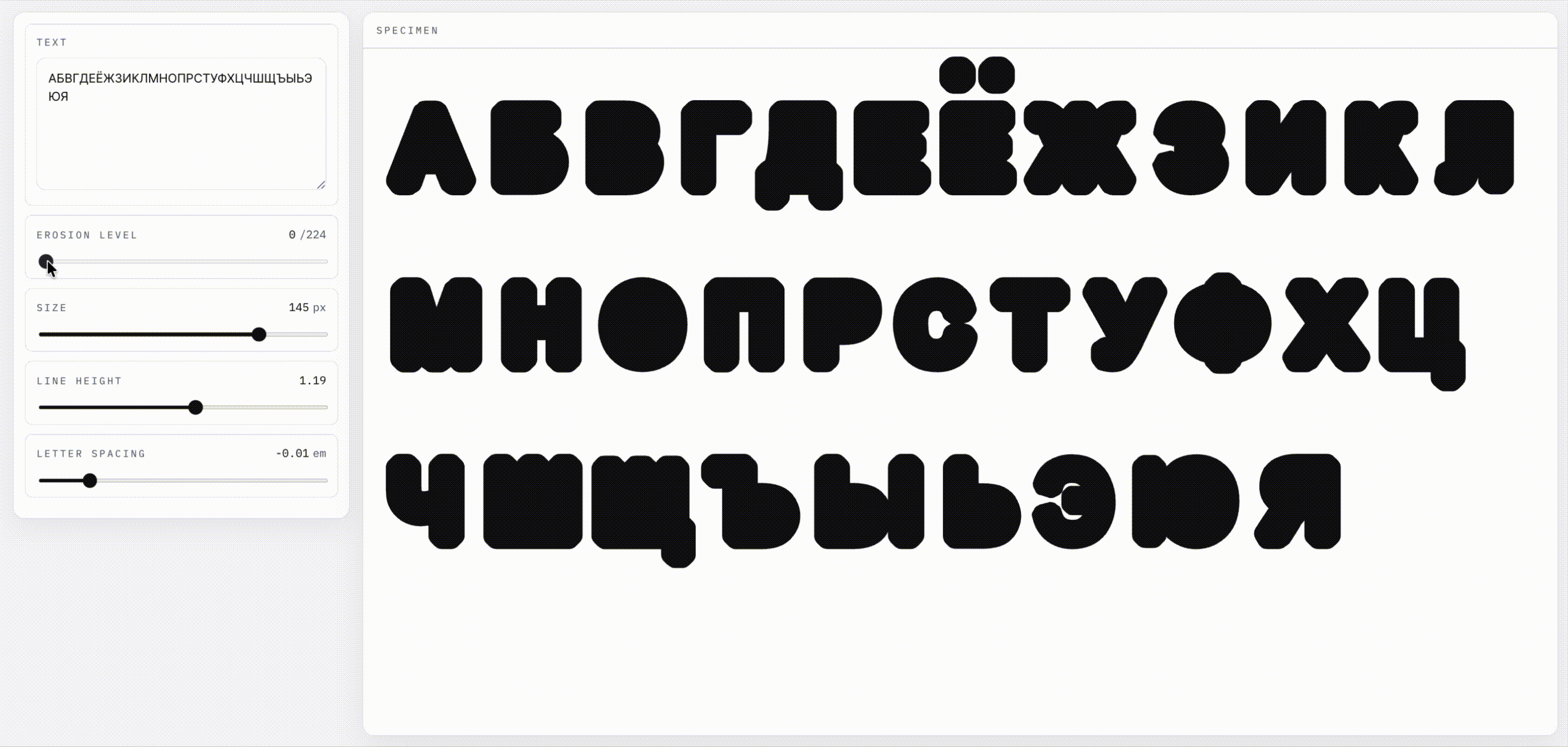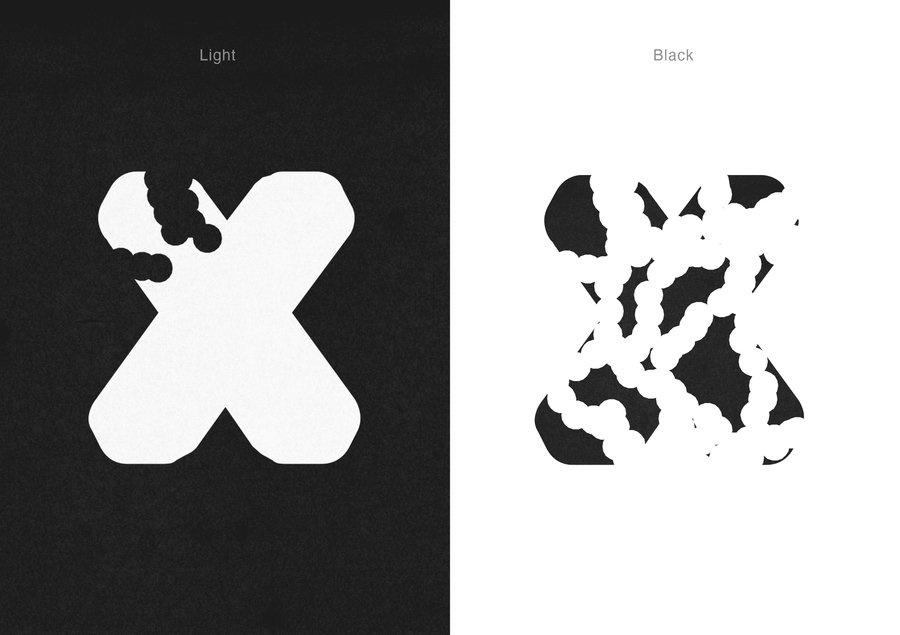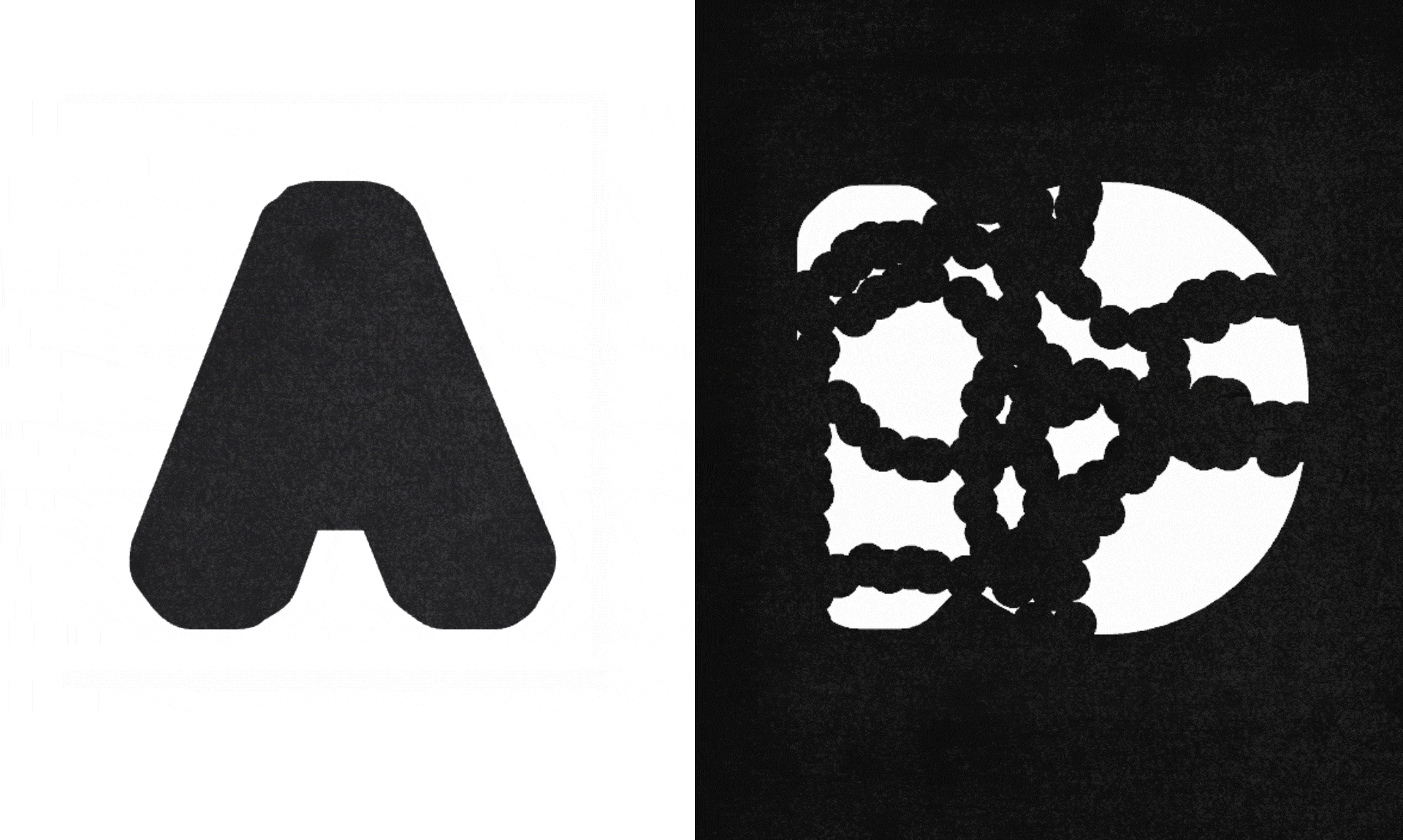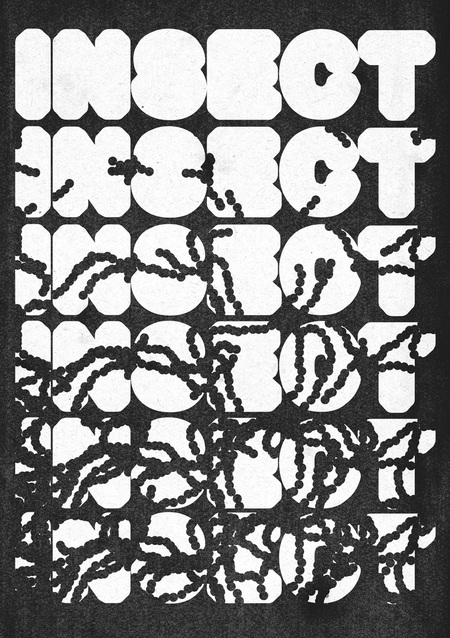
Буква — это органическая поверхность внутри которой проходит жизнь, она нестатична. Шрифт вдохновлён тем, как природа съедает материю. Он отражает состояние биологического материала в процессе изменений.
Шрифтовая основа
Шрифт использует биологические сценарии «разъедания», подсмотренные у термитов, минеров и гусениц
I принцип: термит
После сборки всех TTF-файлов я разработала HTML-сайт, на котором можно исследовать вариативность шрифта и принципы его трансформации.
II принцип: минер
III принцип: гусеница